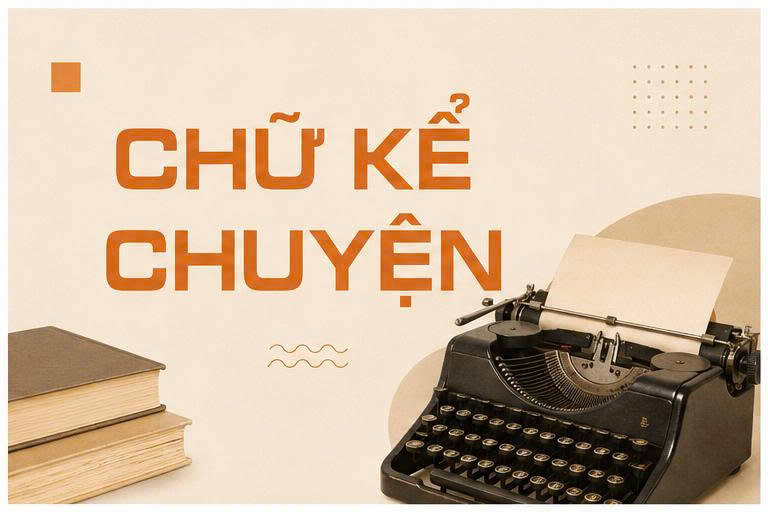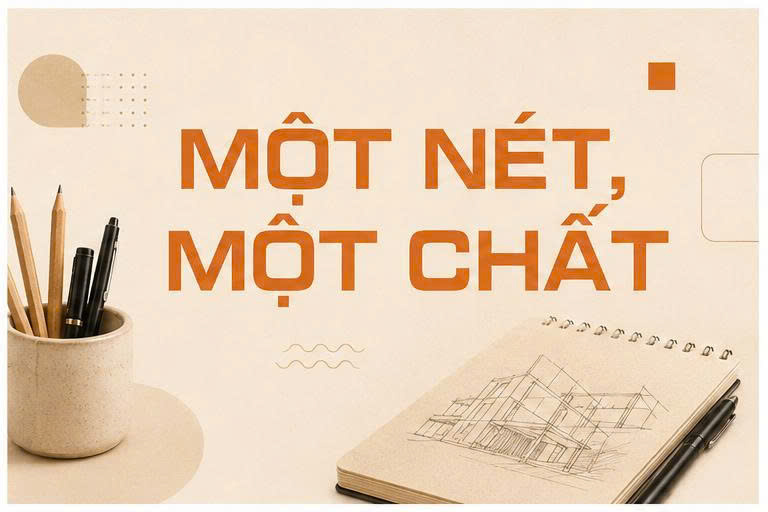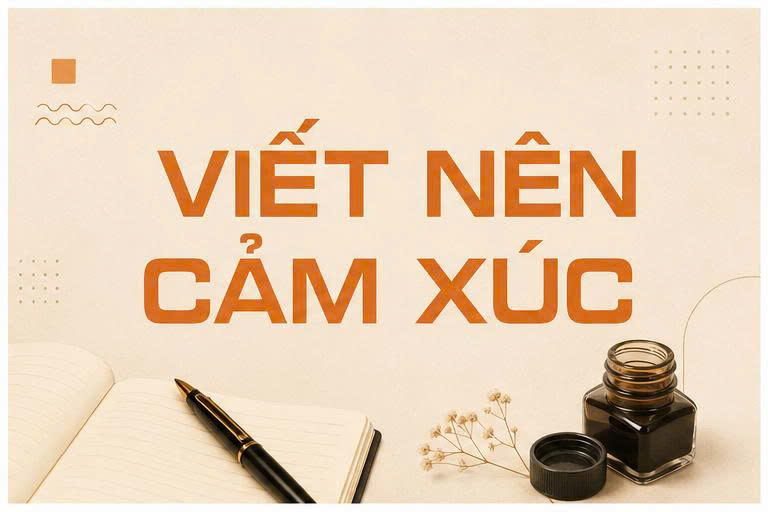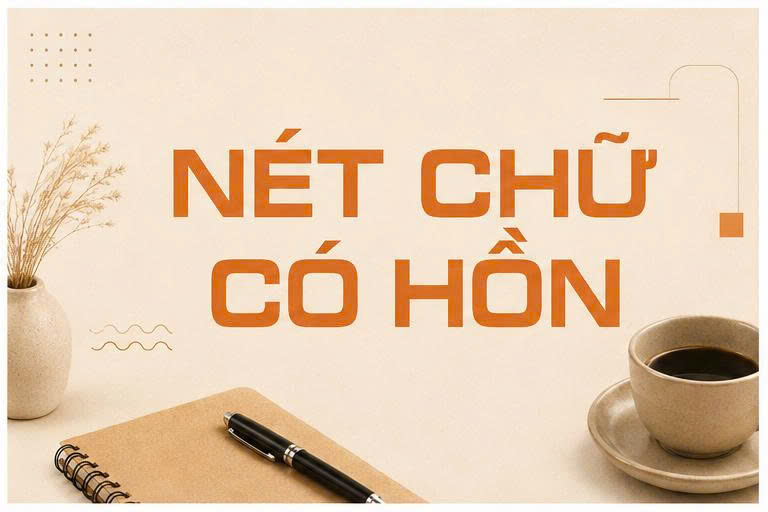
Font Eurostile Việt hóa là bộ phông chữ không chân (Sans-serif) mang tính biểu tượng của phong cách hiện đại và viễn tưởng (Futuristic), được thiết kế bởi Aldo Novarese vào năm 1962. Với đặc trưng là cấu trúc chữ hình vuông bo tròn (squircle), Eurostile toát lên vẻ ngoài vững chãi, minh bạch và đầy tính công nghệ. Đây là lựa chọn hàng đầu cho các thiết kế logo startup, poster phim hành động và đặc biệt là bao bì sản phẩm điện tử cao cấp. Doozypack.vn cung cấp link tải font Eurostile Việt hóa chuẩn, giúp bạn sở hữu bộ phông chữ chỉn chu để nâng tầm diện mạo chuyên nghiệp cho thương hiệu.
Đặc điểm thiết kế độc đáo của bộ font Eurostile Việt hóa
Eurostile không chỉ đơn thuần là một phông chữ hiện đại; nó là kết quả của sự nghiên cứu về hình khối hình học để tạo ra trải nghiệm thị giác mạnh mẽ nhất.
Cấu trúc chữ “Squircle” đặc trưng
Đặc trưng lớn nhất của font Eurostile Việt hóa là các ký tự như ‘o’, ‘c’, ‘d’ không được thiết kế theo hình tròn tuyệt đối mà có dạng hình vuông bo tròn nhẹ ở các góc. Thiết kế này tạo nên sự cân bằng hoàn hảo giữa tính kỷ luật của máy móc và sự mềm mại của đồ họa hiện đại. Phong cách này giúp tiêu đề bản thiết kế của bạn trông vô cùng vững chãi và hiện đại, gợi nhắc đến những bảng điều khiển kỹ thuật cao.
Khả năng hiển thị sắc nét trên mọi nền tảng
Eurostile sở hữu các nét chữ có độ dày đồng đều và khoảng trống trong chữ (counter) rộng rãi. Đặc điểm kỹ thuật này giúp mắt người dễ dàng nhận diện mặt chữ ngay cả khi hiển thị ở độ phân giải thấp trên màn hình hoặc khi in ở kích thước nhỏ trên tem nhãn. Bản Việt hóa tại Doozypack.vn đảm bảo bộ font Eurostile tiếng Việt được xử lý dấu thanh tinh tế, không làm mất đi độ thoáng đặc trưng của font.
Tại sao designer nên chọn font Eurostile Việt hóa cho thiết kế bao bì?
Trong ngành sản xuất bao bì tại Doozypack.vn, Eurostile luôn nằm trong danh mục các font chữ “quyền lực” nhờ tính ứng dụng thực tế cao:
- Hoàn thiện nội dung tiếng Việt: Việc sử dụng bản Việt hóa chuẩn giúp bạn gõ các tiêu đề như “Công nghệ dẫn đầu”, “Sản phẩm chất lượng” một cách trọn vẹn, các dấu thanh được tinh chỉnh mượt mà, không bị thô hay đè nét.
- Tạo dấu ấn đẳng cấp và hiện đại: Vẻ ngoài của Eurostile mang hơi thở của các thương hiệu công nghệ và công nghiệp toàn cầu, giúp bao bì toát lên vẻ uy tín và tân thời.
- Phân cấp thông tin linh hoạt: Với đầy đủ các biến thể từ Extended (rộng) đến Condensed (hẹp), Eurostile giúp designer dễ dàng sắp xếp nội dung trên những bề mặt bao bì có diện tích khác nhau.
| Biến thể Font | Đặc điểm thị giác | Ứng dụng đề xuất tại Doozypack.vn |
| Eurostile Regular | Cân đối, hiện đại | Dùng cho bảng thành phần, hướng dẫn sử dụng sản phẩm. |
| Eurostile Bold | Vững chãi, nổi bật | Dùng làm tiêu đề chính, tên sản phẩm hoặc logo thương hiệu. |
| Eurostile Extended | Rộng, thu hút | Dùng cho tiêu đề trên các túi giấy hoặc hộp quà tặng bản lớn. |
Tư vấn từ chuyên gia: Nếu bạn thiết kế tiêu đề cho hộp sản phẩm điện tử, hãy ưu tiên dùng biến thể Eurostile Bold Extended. Cấu trúc chữ rộng và đậm của nó sẽ giúp tên thương hiệu nổi bật tuyệt đối trên kệ hàng, tạo cảm giác về một sản phẩm cao cấp và quyền lực.
03 Ứng dụng của font Eurostile trong sản xuất bao bì tại Doozypack.vn
Sự hiện đại và mạnh mẽ của Eurostile mang lại hiệu quả thị giác đặc biệt trên các ấn phẩm thực tế do Doozypack.vn sản xuất:
- Hộp sản phẩm công nghệ: Nét chữ hình học của Eurostile rất tương đồng với các thiết kế linh kiện điện tử, tạo nên sự đồng bộ chuyên nghiệp từ sản phẩm đến vỏ hộp.
- Túi giấy doanh nghiệp: Tên công ty in bằng Eurostile Bold trên túi giấy Ivory cán màng mờ tạo cảm giác vững chắc và đáng tin cậy.
- Tem nhãn thông số kỹ thuật: Cấu trúc rõ ràng của Eurostile giúp các bảng thông số trên tem decal trở nên dễ tra cứu và thẩm mỹ hơn.
Lưu ý kỹ thuật khi in ấn với phông chữ hình học hiện đại
Sản xuất bao bì sử dụng phông chữ đặc thù như Eurostile đòi hỏi designer cần lưu ý một số vấn đề kỹ thuật tại xưởng in chuyên nghiệp:
- Khoảng cách chữ (Tracking): Do cấu trúc chữ Eurostile hơi rộng bản, bạn nên điều chỉnh khoảng cách thủ công (khoảng +10 đến +20) để tránh việc văn bản trông quá dính nhau khi in Offset trên giấy Kraft.
- Kiểm soát kích thước chữ tối thiểu: Trên chất liệu giấy Ivory nhẵn mịn, Eurostile vẫn rõ nét ở 5.5pt. Tuy nhiên, trên giấy nhám, bạn nên để tối thiểu là 7pt để đảm bảo các dấu tiếng Việt không bị nhòe.